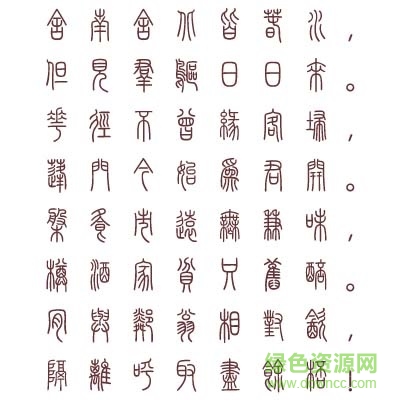
軟件介紹 軟件標簽: 漢儀字體 篆書 字體 漢儀篆書簡體是一款有著清新風格的漢儀字體,大氣簡潔的造型讓你的廣告設計、文字排榜更有特色,綠色資源網(wǎng)歡迎大家下載免費版!字體安裝方法1.在綠色資源網(wǎng)下載字體包,并解壓縮2.雙擊字體文件,點擊安裝即可(適合安裝單個字體)3.將字體文件復制到C:\WINDOWS\Fonts(適合同時安裝大量字體) 漢儀篆書簡體還未推出,敬請期待。本字體如果商用,請聯(lián)系漢儀字體官方獲得授權。 軟件截圖 上一張下一張(1 / 1) 安裝詳細截圖 猜你喜歡 篆書字體 篆書字體 篆書是最早的一種書體,這款字體有著中國悠久歷史的文化氣息,方筆、圓筆、尖筆是篆書的共同特點,從周代時期,篆書就開始形成雛形,隨著歷史的發(fā)展,篆書也在不斷變化,每個時期都有其自身的特色,現(xiàn)在的漢字就是有小篆演變而來。風格渾厚樸茂的篆書字體也受到廣發(fā)歷史研究者的喜愛,這里包含了篆書字體大全,有需要的朋友歡迎來綠色資源網(wǎng)下載體驗! 查看更多>> 手機篆體字 31.25M/中文/5.0/v3.1 安卓版下載 篆書查詢軟件 24.52M/中文/5.0/v7.5 安卓手機版下載 方圓印章篆體 2.44M/中文/6.6/下載 青銅器銘文字體 4.08M/中文/6.6/下載 富漢通粗印篆體繁字體 14.40M/中文/5.0/下載 fcuzuan(迷你繁篆書) 2.44M/中文/5.0/ttf免費版下載 其他版本下載 標題 大小 更新日期 下載 下載地址 電腦版 點擊報錯 軟件無法下載或下載后無法使用,請點擊報錯,謝謝! 關閉報錯反饋 請描述您所遇到的錯誤,我們將盡快予以修正,謝謝! *必填項,請輸入內容 本類最新 漢儀孟瑞體ttf v1.0 官方版 漢儀字庫免費 132款 阿里巴巴普惠字體 官方ttf版 漢儀字體打包大全 for Mac 蘋果電腦版_ 共131款字體 漢儀純愛情書拼音體 ttf版 漢儀北魏寫經(jīng)w字體 免費版 相關文章 Photoshop字體安裝使用方法和技巧 如何解決“無法新增字體”問題 Win 7系統(tǒng)安裝字體方法 網(wǎng)頁字體大小設置方法 怎么改網(wǎng)頁字體大小 在Linux系統(tǒng)中安裝字體的幾種方法 windows7字體顯示問題:打開某些程序的時候顯示的是亂碼 用戶評論 熱門評論 最新評論 發(fā)表評論 查看所有評論(0) 昵稱: 請不要評論無意義或臟話,我們所有評論會有人工審核. 字數(shù): 0/500 (您的評論需要經(jīng)過審核才能顯示)